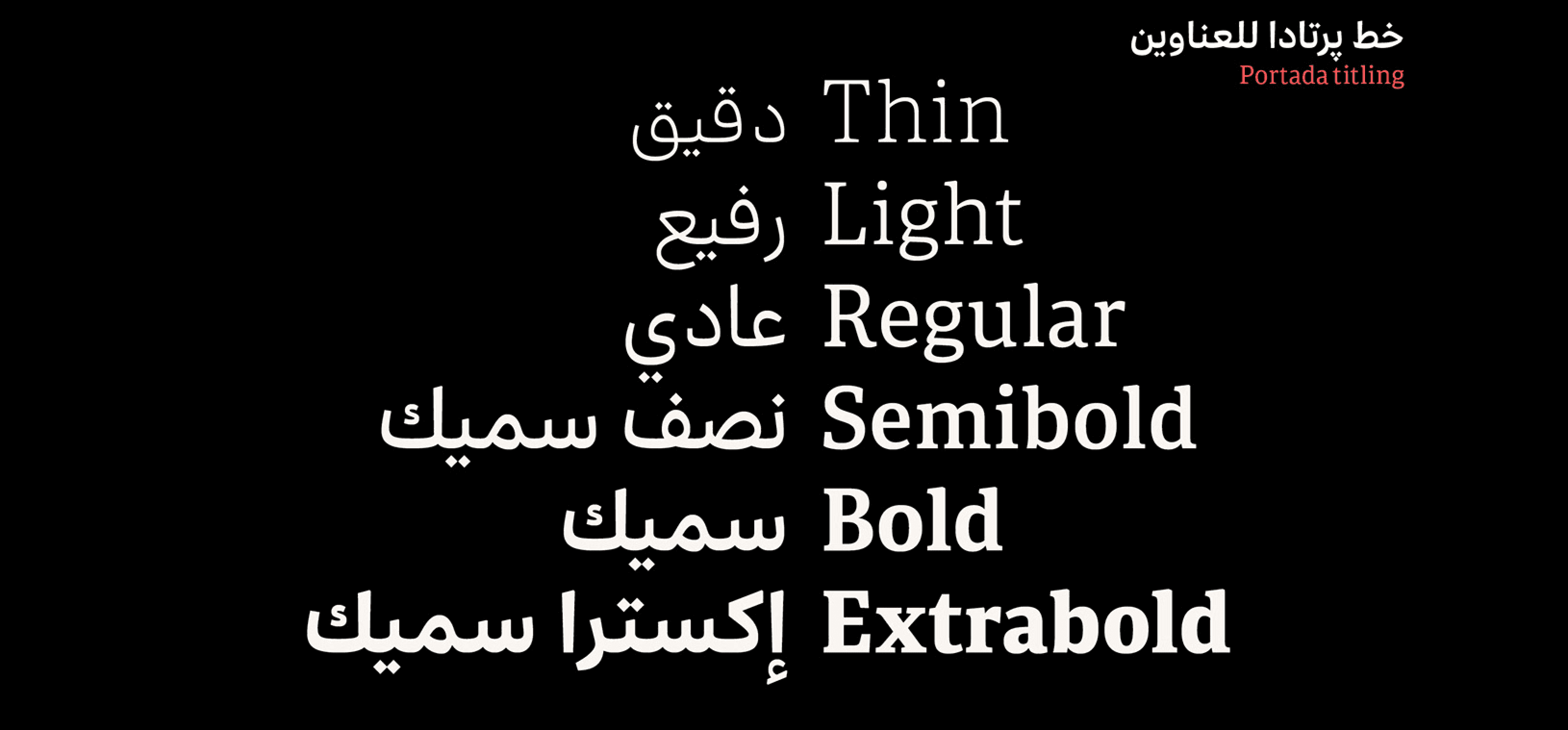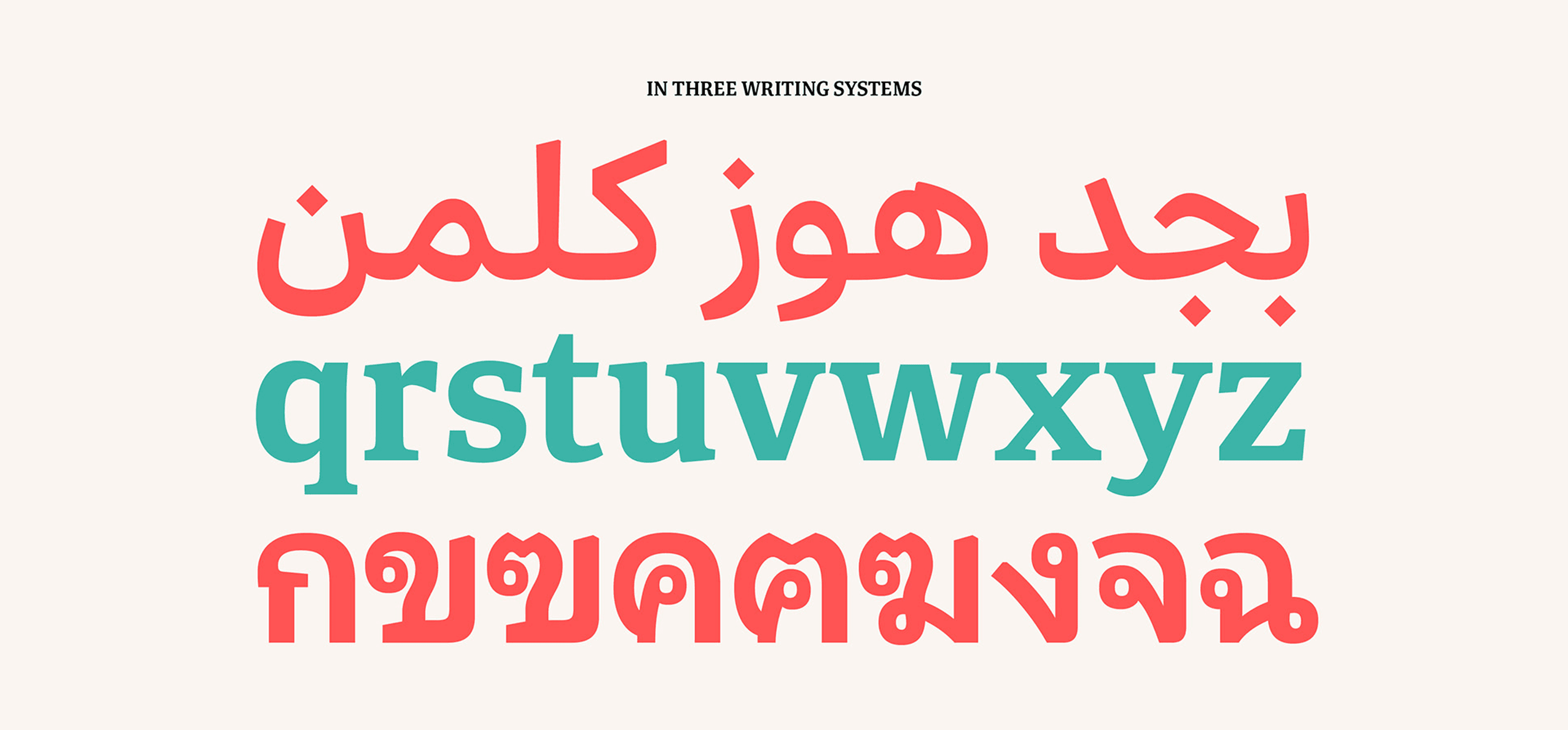
عائلة خطوط Portada حازت مسبقًا على عدة جوائز، واستُخدمت في مجموعة واسعة من التطبيقات، من المجلات والعلامات التجارية لشركات الطيران الدولية إلى مواقع الويب والنصوص الرقمية.
واليوم نُعلن عن إطلاق Portada Arabic من تصميم سحر أفشار. الخط العربي الجديد مستند إلى أسلوب النسخ، ويتبع نفس الهيكل العام لعائلة Portada، حيث يتوفّر بإصدارين: Display وText، بالإضافة إلى إصدار متغير (Variable Font)، ما يمنحه مرونة كبيرة في الاستخدامات الطباعية المختلفة.